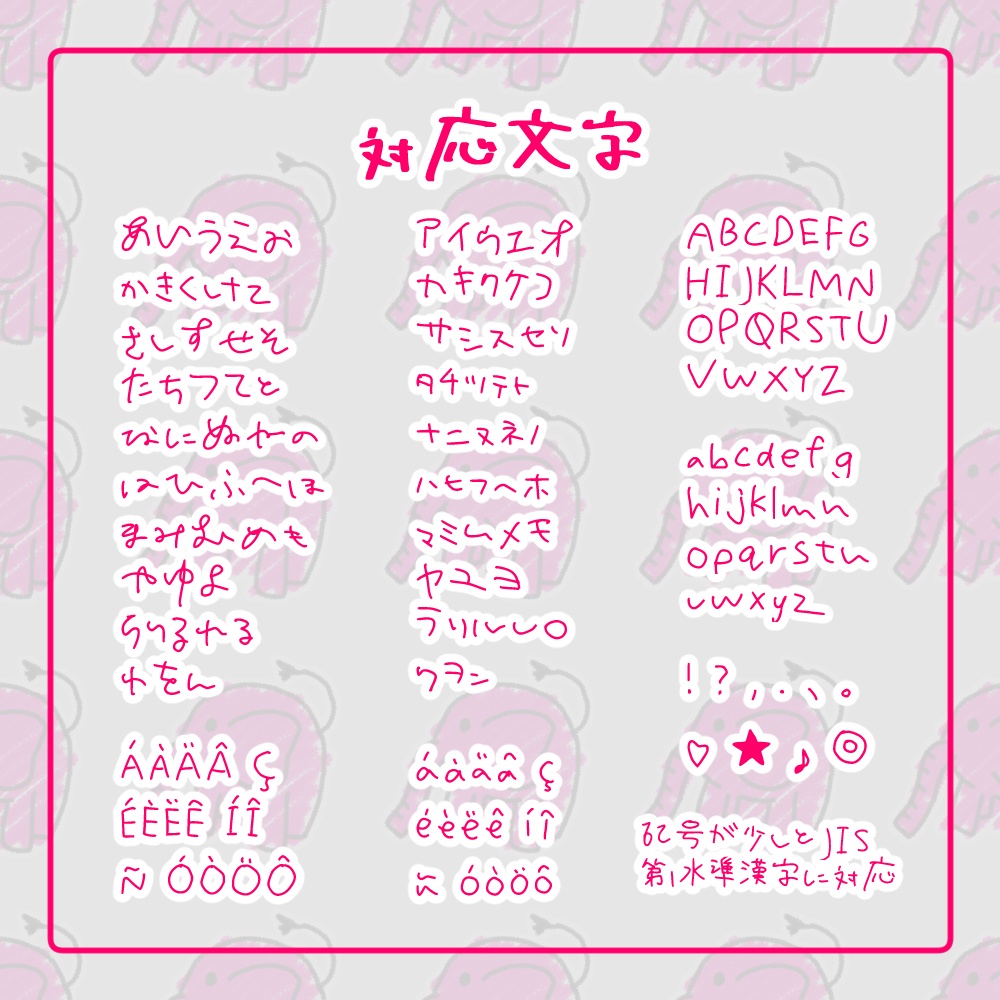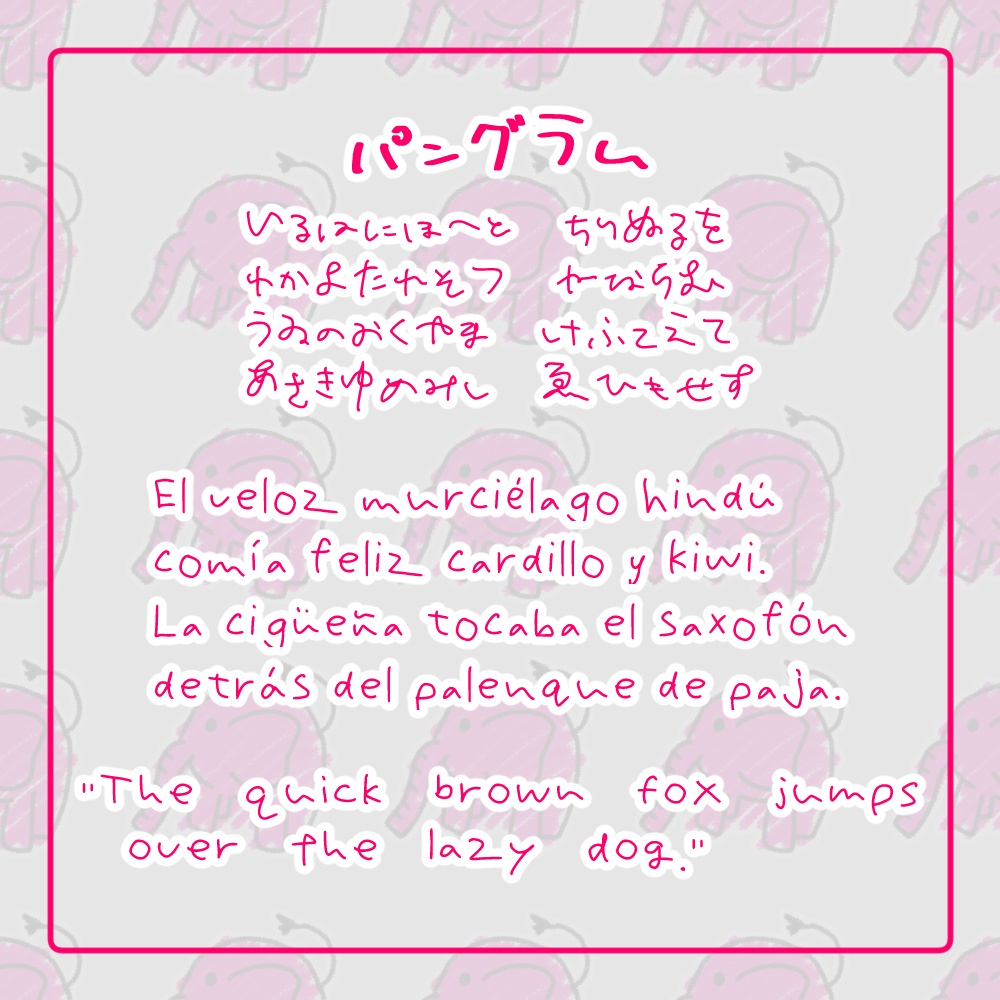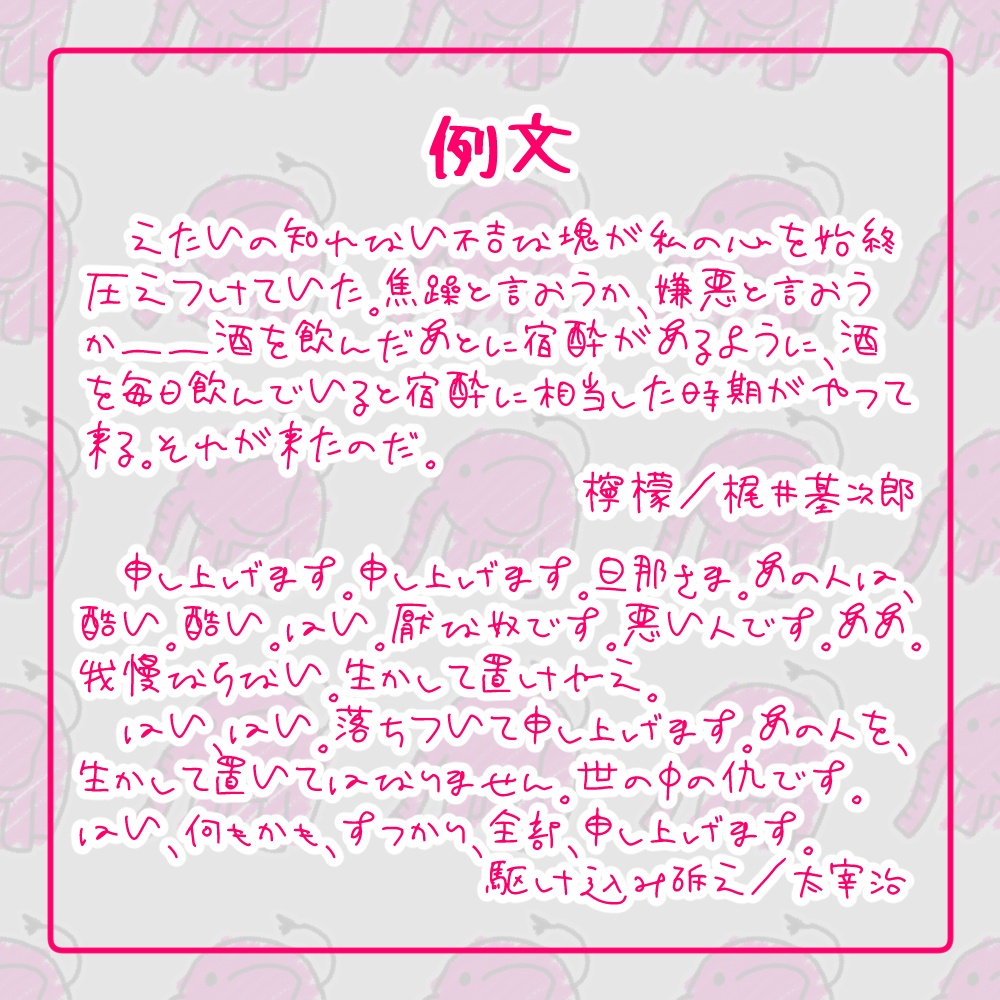
【無料/投げ銭】あさはなふぉんと【フリーフォント】
手書きのフォント「あさはなふぉんと」です。 今後漢字を追加して更新予定です。 商用可・再配布可ですのでゲーム制作の組み込みにも使用できます。 ◾︎あるもの ひらがな、カタカナ、アルファベット、漢字(JIS第一水準+α)、記号 対応言語:英語、スペイン語、ドイツ語 ◾︎内容物 OTF、TTF、イメージ画像、readme 無料版と投げ銭版のフォント内容は同一です。 投げ銭版にはおまけに商品イメージ画像がついています。 脱字・不備等ございましたらお手数ですがお気軽にご連絡ください。 上下さかさまから書いた「さかさまふぉんと」も出ました。 https://9yud9.booth.pm/items/6061703 以下の配信内で作成しました。 https://www.youtube.com/live/8U7O6vPzXTo?si=fkS4rRB8npISI-10